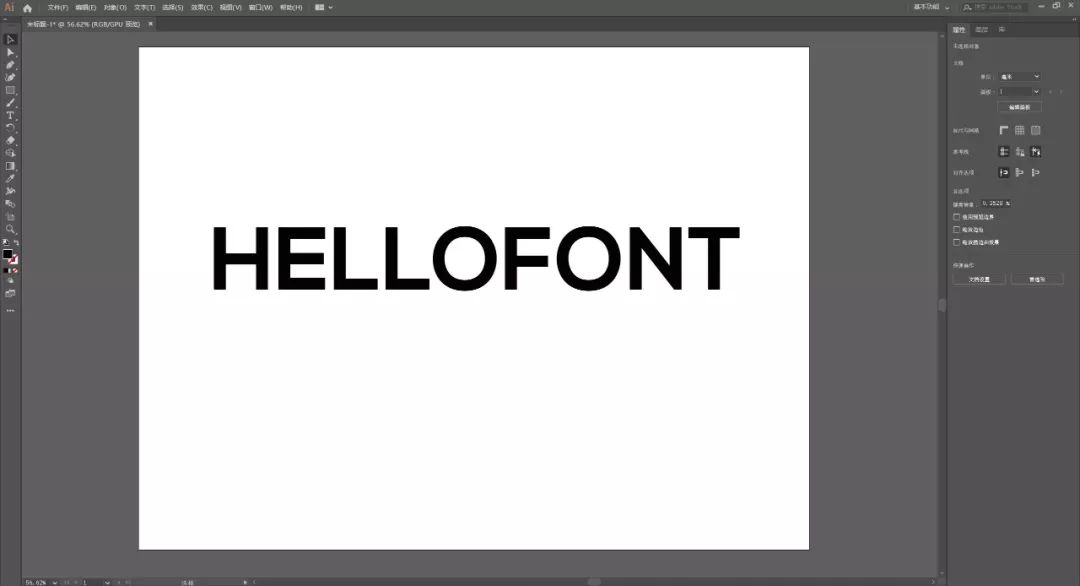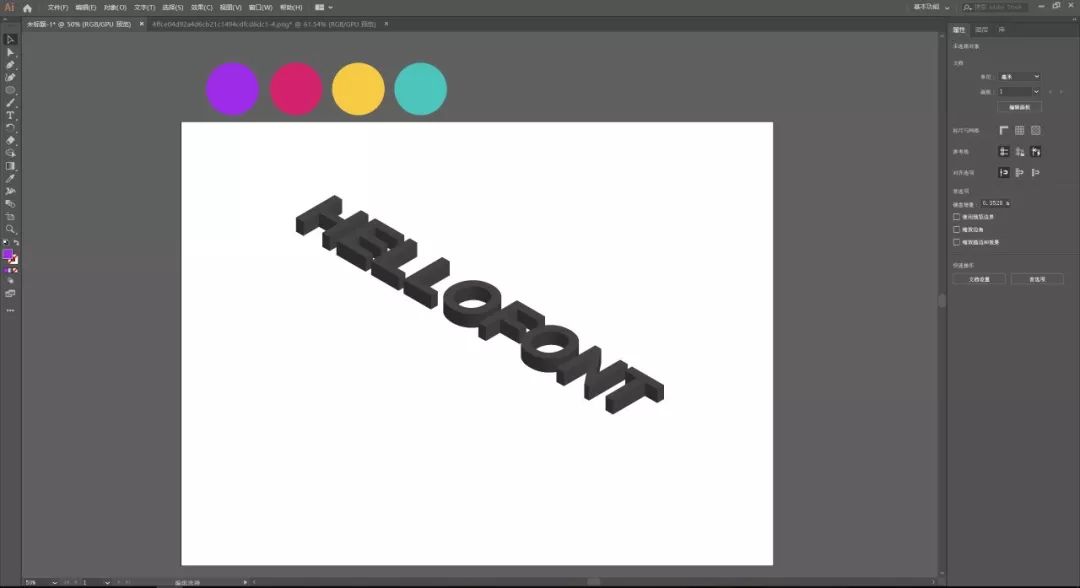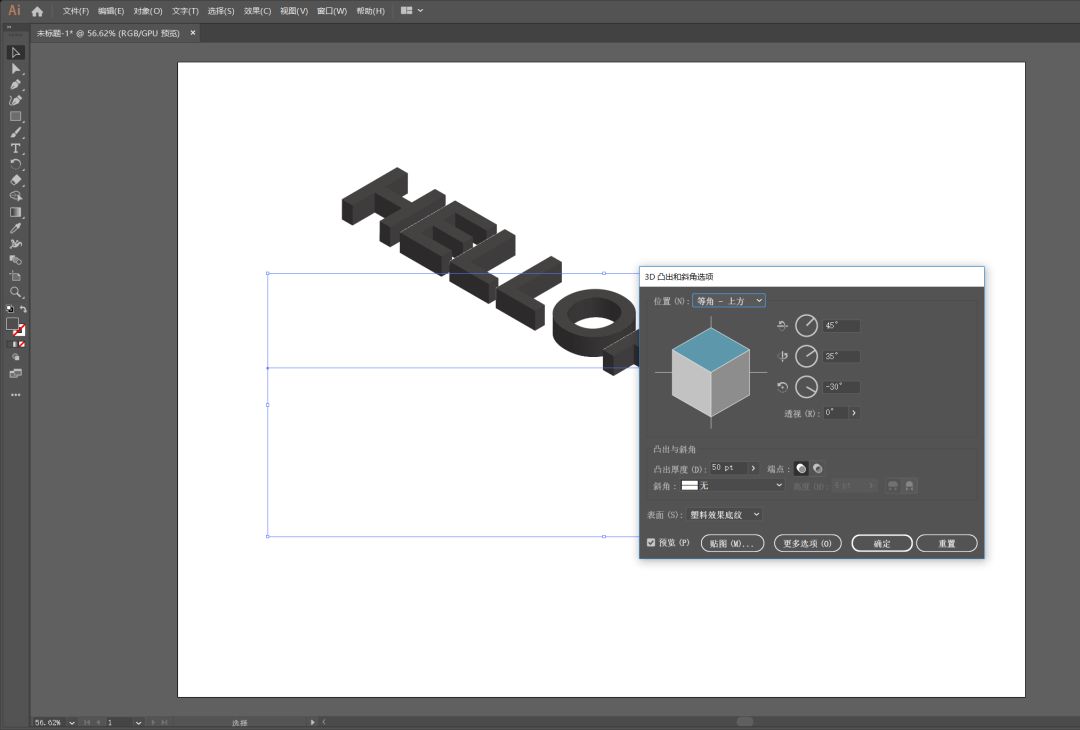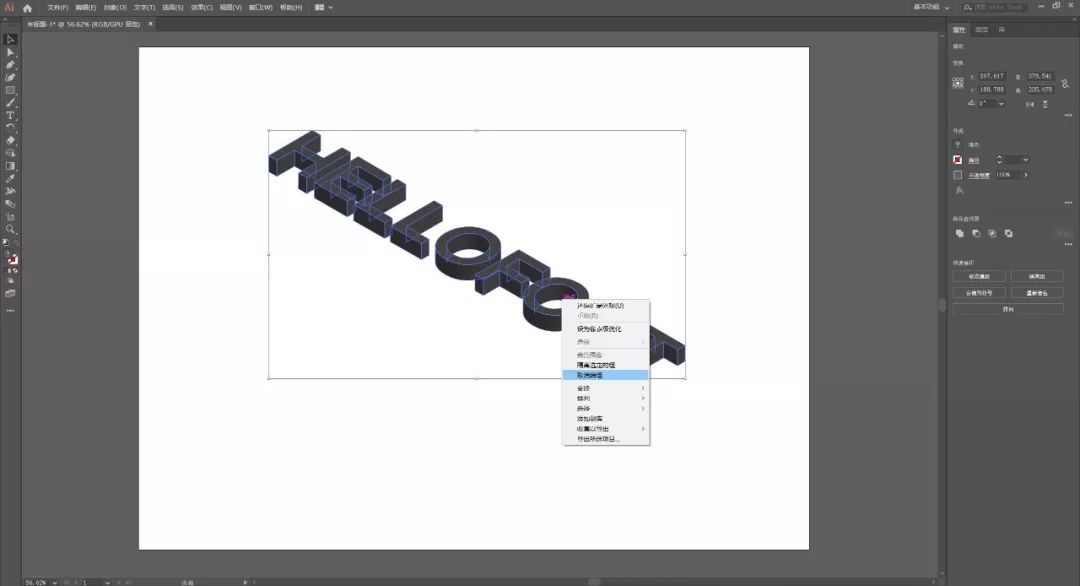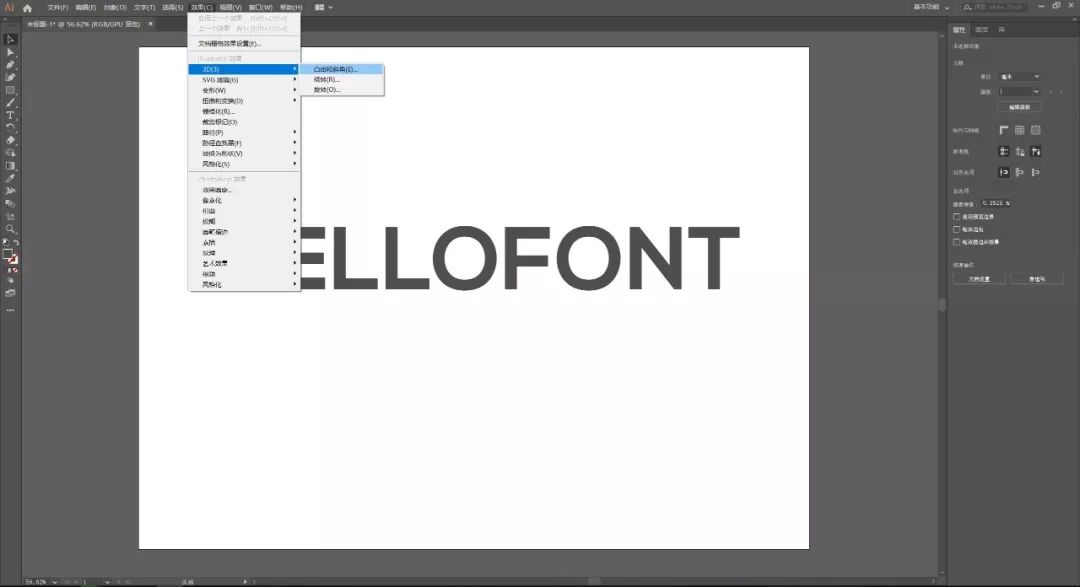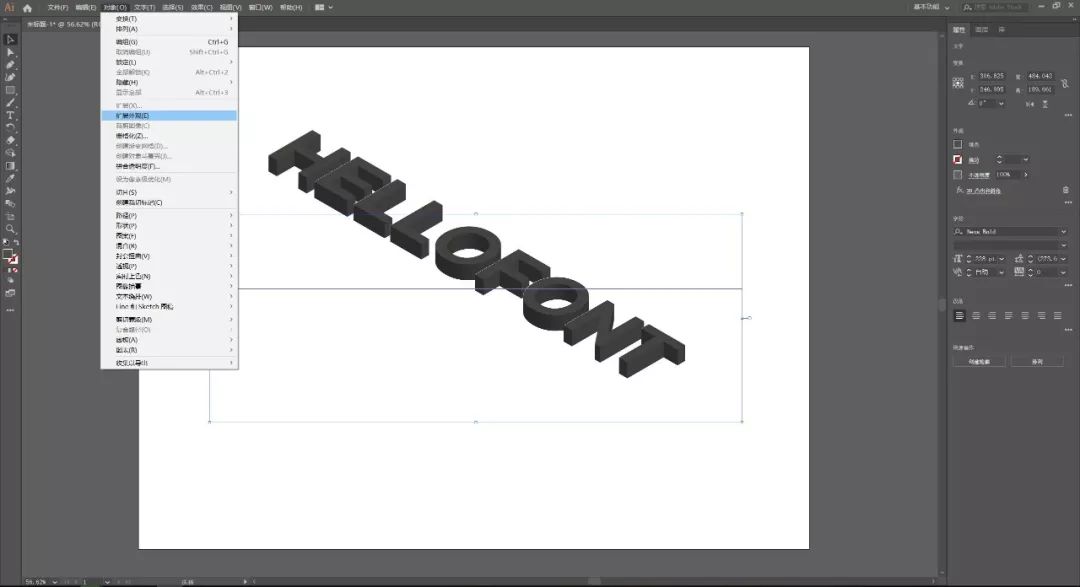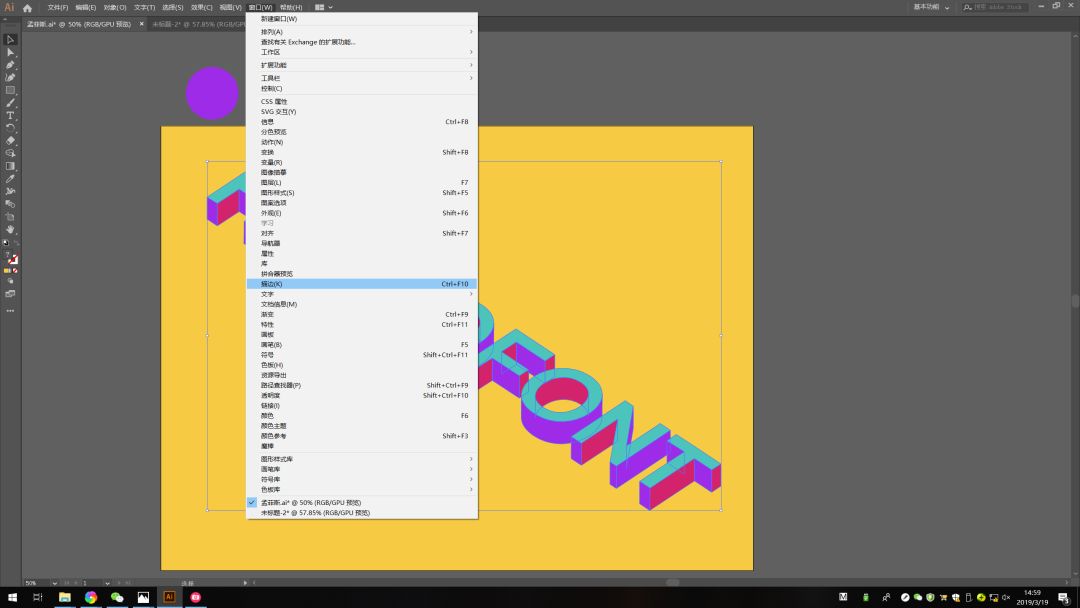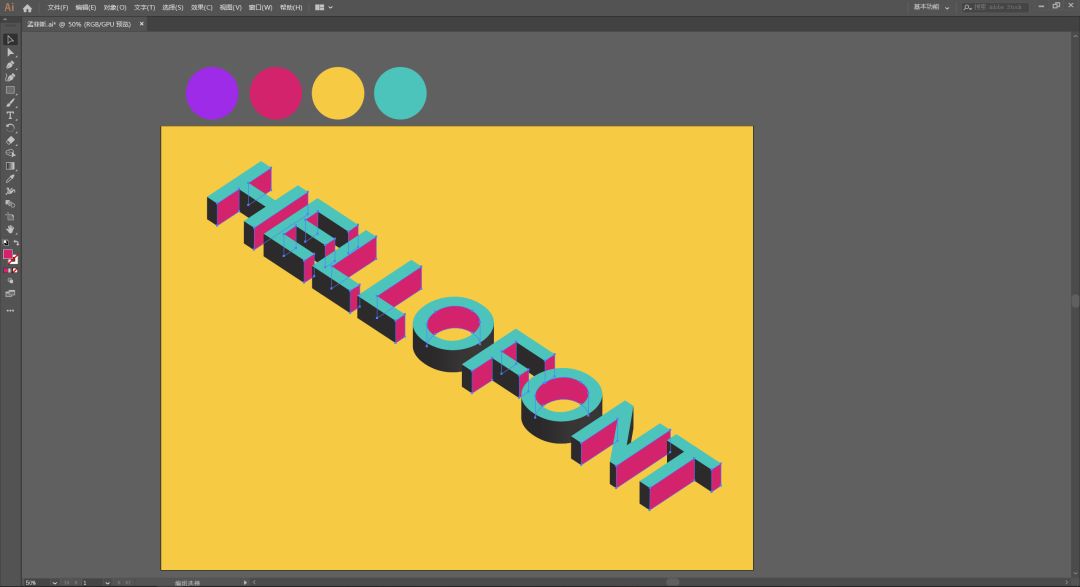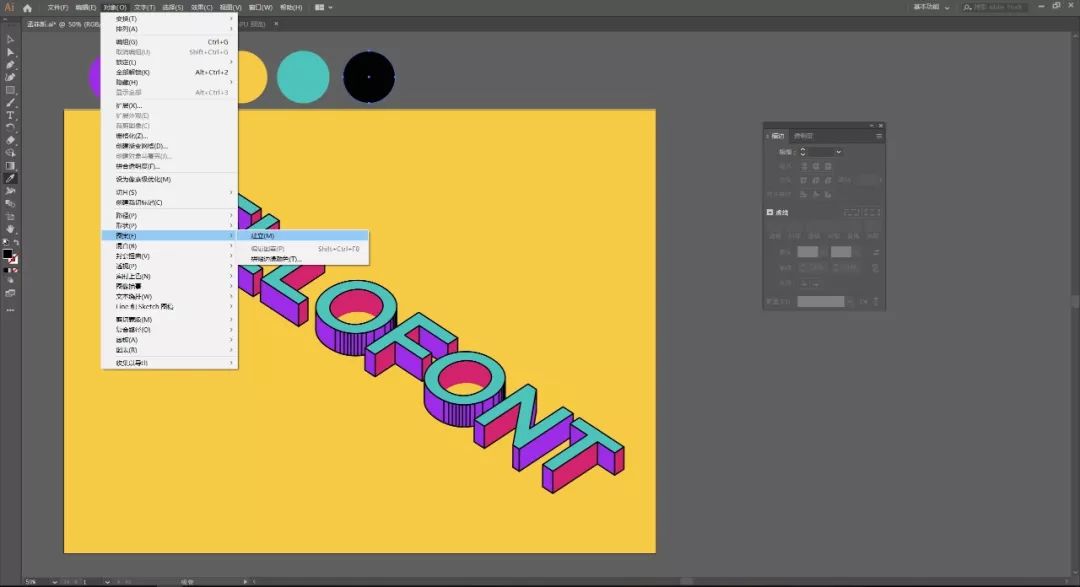
孟菲斯不好驾驭?那就手把手教你用AI做一个~
之前在OMG,这样的配色也太减龄了吧!说过孟菲斯风格,很多人都觉得很好看,但不好驾驭!
所以今天是第二课,手把手教你做一个孟菲斯的字体效果,快来学习~
在AI中创建一个新文档,并输入文字。这里我用的是字由上的Nexa Bold,别的字体也可以,只是注意不要太细。
将文本填充成灰色(不然就是糊的哦),然后效果> 3D>凸出和斜角。
选择等角-上方,其他参数不用改。
接着选中文字,点对象> 扩展外观。
接着鼠标右键取消编组~
将整体的3D图形转换成单独的块面。
选一组好看的孟菲斯配色,放一边吸色~
建一个画布大小的矩形,填充黄色。
然后按住shift,把正面填充绿色。
接着在稍浅的块面填充红色,更深一点的填充紫色(我用的是AI2019,弧形部分会自动识别,其它版本的要记得路径查找器>联集)。
现在要进行描边了,背景总会出来捣乱,所以可以先点击黄色矩形,再对象>锁定,就可以框选“hellofont”了,再窗口>描边。
注意啊,一定要看你左边工具栏的描边有没有选色,不然就会出来白的,我大概调了3pt,边角为圆角连接,其它都默认。
如果觉得哪的描边多余,可以点击形状,然后左边菜单栏选择无,这里我主要是孟菲斯风格,需要有线条,所以就去掉一部分吧~
到这一步基本完成,但别忘了,上次我说过,点点点也是灵魂所在,所以我们再精细一点。
直接从上面四个圆形,按住shift+alt,复制一个,并填充黑色。
把黑色调小至2mm左右(在图片上看就是一个点),再对象>图案>建立。
选择砖形(按行),宽度和高度设为5mm,调节圆点间距。
点击紫色块面,再窗口>外观>填充新填色,选择刚刚自己制作的点点图案,把它都加上(亲测黑点一定要小,不然就会出现一大坨,或者豹纹)。
最后再来个投影,选择顶面并按ctrl+c和ctrl+f复制并粘贴在前面(ctrl+b是粘贴在后面),将其填充为黑色,并编组。
再复制一层,将其轻推到左侧,形成错位,然后对象>混合>建立,在混合选项中,将“间距”更改为“指定的步数”,并增加到100。
转到对象>扩展,然后使用“路径查找器”,将所有部分联合起来,移到黄色背景之上,透明度降到10%,就可以了。